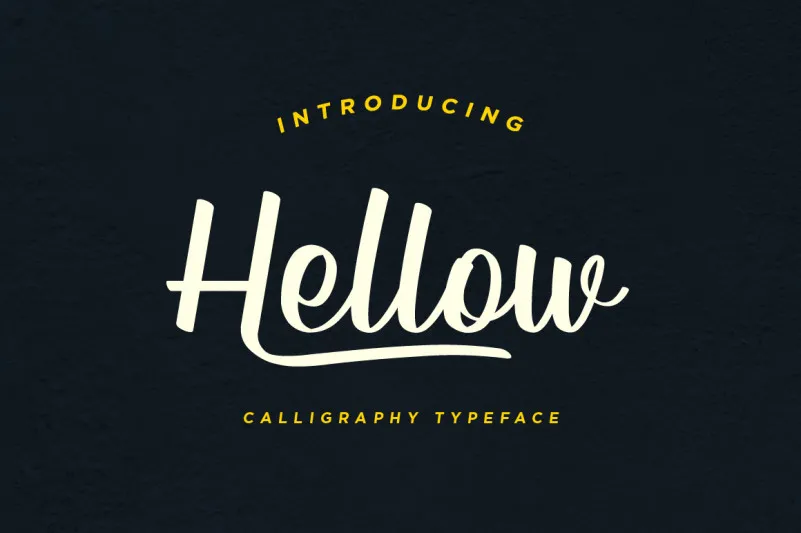
Hellow – Calligraphy Typeface – Download Grátis
Esta fonte é perfeita para quem gosta de design jovial e apaixonado, ideal para aplicar em projetos como logos, camisetas, identidades corporativas e muitos outros usos gráficos. Seja você designer ou alguém que quer criar sua própria marca, a Hellow – Calligraphy Typeface é perfeita para atender às suas necessidades. O grande mérito desta fonte é seu suporte em diversas técnicas de impressão. Ela se destaca em papéis de qualquer espessura, inclusive tecidos e peles sintéticas para embossagem, além de ser capaz de se adaptar à bordados e outros métodos de impressão modernos. Com Hellow – Calligraphy Typeface, suas marcas corporativas ficam ainda mais sólidas e fortes em qualquer meio ou material. Indicada para designers inovadores que buscam uma fonte única para seus projetos criativos, a Hellow – Calligraphy Typeface é um verdadeiro complemento ideal para quem procura expressar sua marca de maneira elegante e personalizada. Tudo isso sem perder seu charme clássico da tipografia gráfica tradicional.